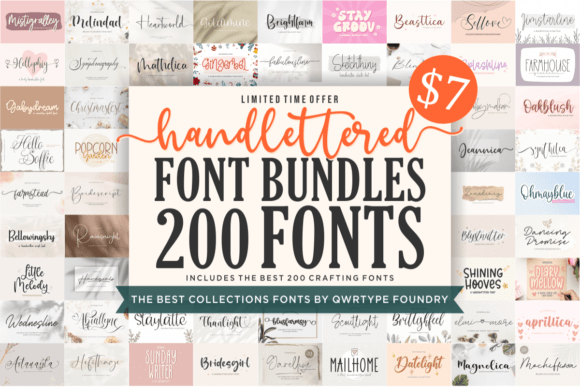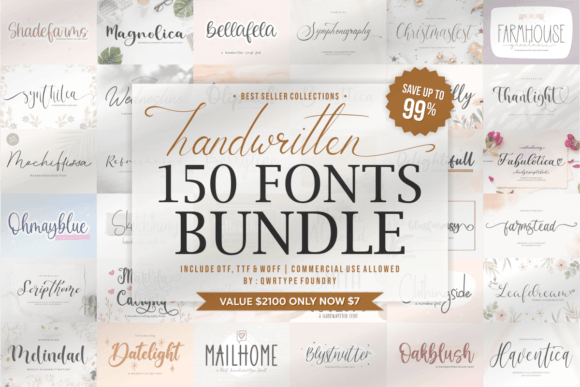
Hand Lettered Font Bundle
Si buscas recursos de alta calidad como Hand Lettered Font Bundle, este paquete premium es una opción fantástica para tus proyectos creativos.
Ya sea que estés creando productos POD (impresión bajo demanda), invitaciones de boda o gráficos para redes sociales, Hand Lettered Font Bundle es una opción ideal.